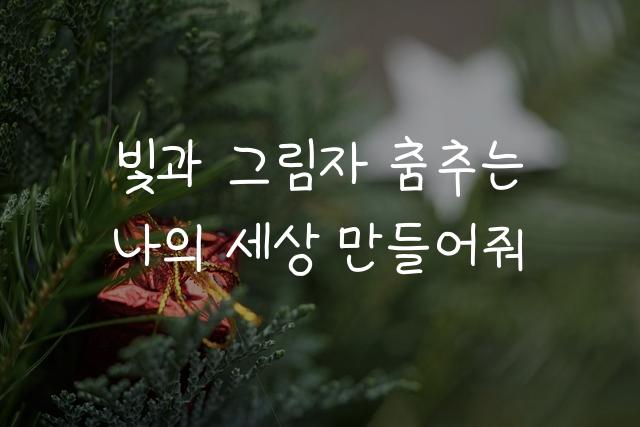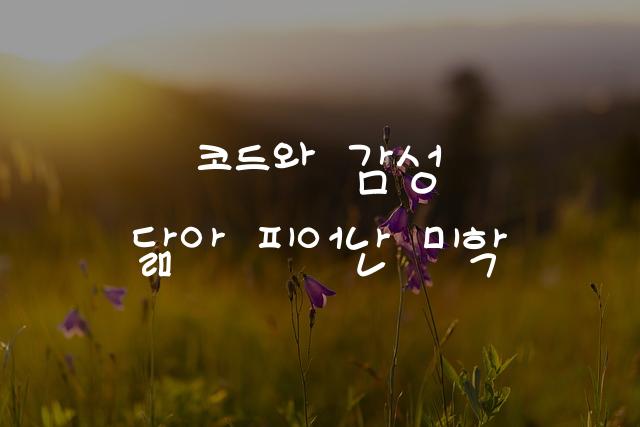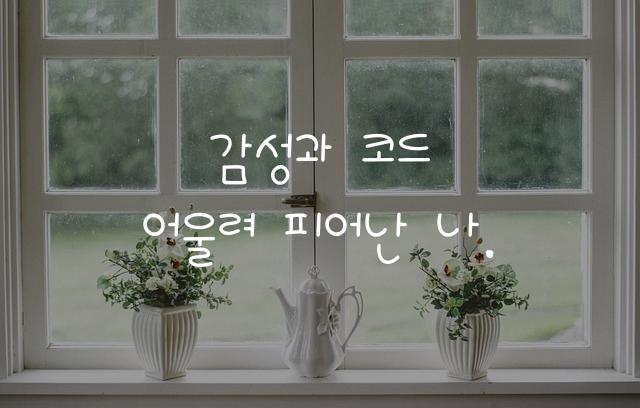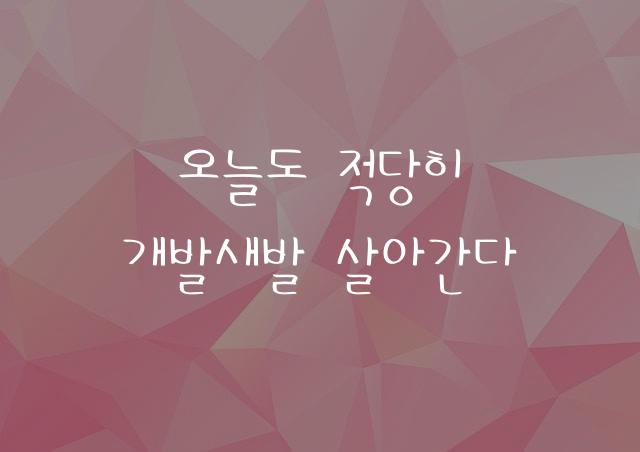
조군 개발새발 V5는 독특하고 동글동글한 특징을 가진 한국어 폰트로, 둥근 형태가 주는 부드러움과 함께 독창적인 디자인이 돋보입니다. 이 폰트는 개성적인 문서나 디자인 작업에 적합하여 창의적인 표현을 가능하게 합니다.
조군 개발새발 V5은(는)
둥근 스타일, 감성적인, 자연감성, 부드러움, 복실복실 계열의 생김새를 가지고 있으며
웹/앱 디자인, 프레젠테이션, 보고서/문서 등에서 자주 활용되며, 효과적인 메시지 전달에 적합합니다.
이 폰트는 크리에이티브, 기술/IT, 금융/비즈니스 분야에 잘 어울리며,
명확한, 창의적인, 전문적인 느낌을 담고 있는 것이 특징입니다.
이 폰트와 유사한 폰트로는 새롬체, 고딕체, 바른펜체 등이 있어요. 함께 비교해 보시면 좋습니다!